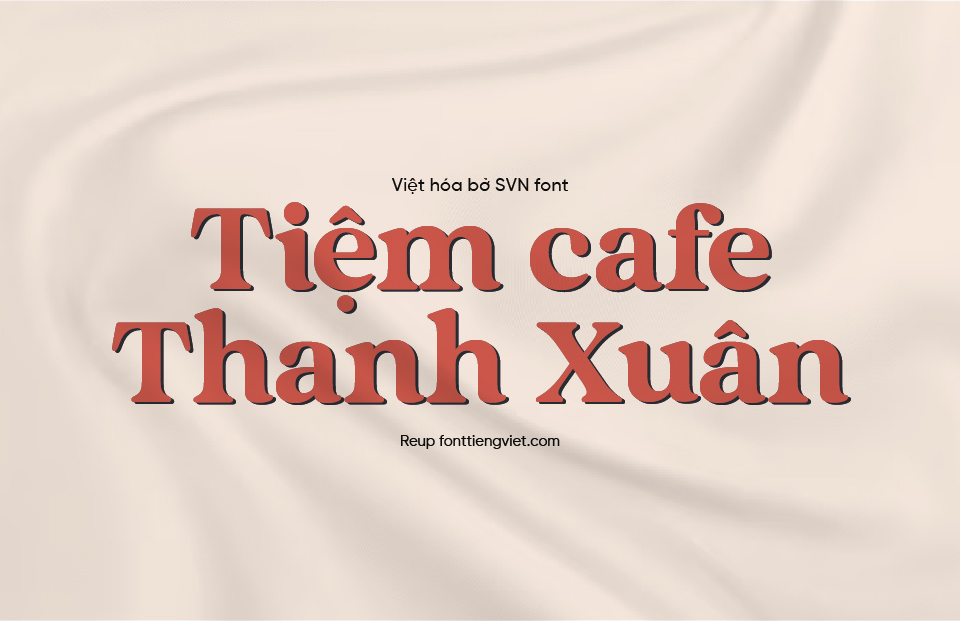
Tải Ngay Font Việt hóa SVN Vintage – Đỉnh Cao Phong Cách Cổ Điển Cho Thiết Kế
Trong thế giới thiết kế đồ họa hiện đại, việc sử dụng các mẫu Font Chữ mang đậm nét hoài cổ đang trở thành xu hướng mạnh mẽ. Font Việt hóa SVN Vintage là một trong những bộ phông chữ được yêu thích nhất nhờ khả năng tái hiện vẻ đẹp của những thập niên trước. Với các đường nét tinh tế và uyển chuyển, bộ font này không chỉ giúp tác phẩm trở nên nghệ thuật hơn mà còn mang lại cảm giác gần gũi, thân thuộc cho người xem tại Việt Nam.
Khám phá đặc điểm nổi bật của Font Việt hóa SVN Vintage
Sự kết hợp giữa truyền thống và hiện đại
Font Việt hóa SVN Vintage được tinh chỉnh kỹ lưỡng để phù hợp với bảng mã tiếng Việt, giúp người dùng dễ dàng sử dụng trong các phần mềm như Photoshop hay Illustrator. Điểm mạnh của bộ font này nằm ở cấu trúc chữ chắc chắn nhưng không kém phần mềm mại, mô phỏng lại phong cách bảng hiệu quảng cáo xưa cũ của Sài Gòn hay Hà Nội thập niên 80. Điều này giúp các dự án thiết kế truyền thông trở nên có chiều sâu và tạo dấu ấn thị giác mạnh mẽ đối với công chúng.
Ứng dụng đa dạng trong nhiều lĩnh vực
Nhờ tính thẩm mỹ cao, Font Việt hóa SVN Vintage thường được các nhà thiết kế ưu tiên sử dụng cho việc tạo logo, bìa sách, menu nhà hàng hay các loại thiệp mời sự kiện. Đối với học sinh và sinh viên, đây cũng là công cụ tuyệt vời để trang trí bài thuyết trình hoặc làm báo tường, giúp nội dung trở nên sinh động và chuyên nghiệp hơn. Sự đa dạng về kiểu dáng trong bộ font cho phép bạn sáng tạo không giới hạn từ phong cách thanh lịch đến bụi bặm, phong trần.